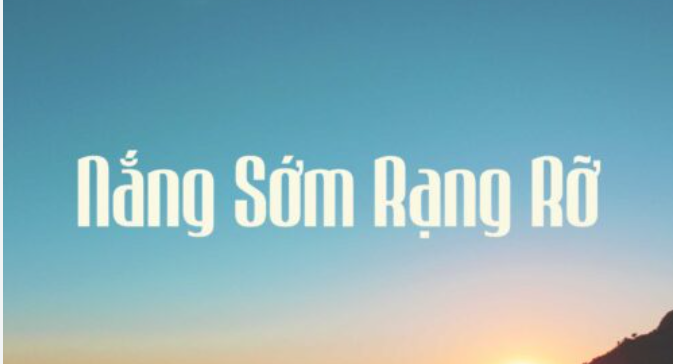
SVN Vantom là bộ phông chữ thuộc dòng Modern Display mang phong cách thanh lịch, thời thượng và tràn đầy hơi thở nghệ thuật đương đại. Với những đường cong uốn lượn sắc sảo, tỉ lệ chữ phá cách kết hợp cùng hệ thống ký tự nối (ligatures) độc bản, phông chữ này là lựa chọn hàng đầu cho các thiết kế logo thời trang xa xỉ, bìa tạp chí danh tiếng và bao bì mỹ phẩm cao cấp. Doozypack.vn cung cấp link tải font SVN Vantom Việt hóa chuẩn kỹ thuật, giúp bạn sở hữu phông chữ đẳng cấp mà không lo gặp bất kỳ lỗi hiển thị dấu thanh nào khi thiết kế in ấn.
Đặc điểm thẩm mỹ độc đáo của bộ font SVN Vantom
Vantom không đi theo sự khuôn mẫu của các phông chữ hình học thông thường; nó mang đến một ngôn ngữ thị giác đầy tính duy mỹ, kết hợp giữa sự tối giản hiện đại và nét mềm mại gợi cảm.
Phong cách Display hiện đại với những đường cong quyến rũ
Đặc trưng lớn nhất của SVN Vantom Font là sự biến tấu tài tình ở những điểm giao nét. Cấu trúc chữ có độ tương phản thanh đậm vừa phải, các nét thẳng đứng vững chãi kết hợp cùng các góc bo mềm mại ở những ký tự như ‘a’, ‘g’, ‘r’, tạo nên một nhịp điệu Typography vô cùng cuốn hút. Khi đặt Vantom làm tiêu đề trên bao bì, thương hiệu của bạn sẽ ngay lập tức toát lên vẻ ngoài sang trọng, đắt tiền và đậm chất thẩm mỹ châu Âu.
Hệ thống ký tự ghép đôi (Ligatures) nghệ thuật và độc bản
Một điểm khiến các nhà thiết kế chuyên nghiệp luôn săn đón font chữ SVN Vantom Font chính là kho ký tự ghép đôi vô cùng phong phú. Phông chữ cho phép bạn liên kết hai hoặc ba chữ cái lại với nhau một cách tự nhiên và liền mạch, biến những dòng chữ thương hiệu đơn giản thành một biểu tượng đồ họa tinh xảo mà không cần phải tốn nhiều giờ chỉnh sửa thủ công.
Ưu điểm nổi bật của bản font Việt hóa SVN Vantom
Khi ứng dụng các phông chữ nghệ thuật quốc tế vào thị trường trong nước, sự chỉn chu về dấu câu là yếu tố quyết định đến tính chuyên nghiệp của bản thiết kế:
- Khắc phục triệt để lỗi dấu tiếng Việt: Phiên bản font Việt hóa SVN Vantom đã được đội ngũ SVN trau chuốt thủ công từng dấu câu. Các dấu sắc, huyền, hỏi, ngã, nặng được vẽ thanh mảnh, đặt ở vị trí cân đối so với thân chữ, không gây cảm giác chắp vá hay va chạm vào các đường nét uốn lượn xung quanh.
03 Ứng dụng thực tế của SVN Vantom Font trong sản xuất bao bì
Sự kiêu sa và thanh lịch của Vantom mang lại hiệu ứng thị giác đắt giá trên các dòng sản phẩm bao bì thực tế do Doozypack.vn sản xuất:
- Hộp giấy mỹ phẩm & Nước hoa: Tên dòng sản phẩm in bằng nét chữ Vantom kết hợp kỹ thuật ép kim nhũ vàng trên giấy Ivory cán màng mờ tạo nên vẻ đẹp sang trọng chuẩn quốc tế.
- Túi giấy thời trang cao cấp: Tiêu đề thương hiệu in bằng font Vantom màu đen tối giản trên nền túi giấy trắng giúp cửa hàng toát lên gu thẩm mỹ tinh tế và đẳng cấp.
- Tem nhãn nến thơm & Tinh dầu cao cấp: Cấu trúc chữ thanh thoát giúp nhãn dán chai lọ trông như một tác phẩm thủ công được chăm chút tỉ mỉ bởi nghệ nhân.
03 Lưu ý kỹ thuật khi in ấn với phông chữ nghệ thuật SVN Vantom
Việc sản xuất bao bì thực tế sử dụng các phông chữ có đường nét tinh xảo như Vantom đòi hỏi sự am hiểu kỹ thuật chuyên sâu tại xưởng in Doozypack.vn:
- Kiểm soát độ dày nét Hairline khi ép kim: Các nét vuốt đuôi nối chữ của font chữ này khá thanh mảnh. Khi gia công ép kim vàng (Hot Stamping), designer nên đảm bảo nét chữ có độ dày tối thiểu 0.15mm để nhũ bám dính sắc nét, không bị đứt đoạn.
- Chọn chất liệu giấy phẳng mịn: Vantom đẹp nhất khi in trên giấy Ivory, Couche hoặc giấy mỹ thuật nhẵn. Tránh in các nét chữ quá thanh trên bề mặt giấy Kraft thô nhám vì mực dễ bị loang làm mất đi độ sắc sảo của nét chữ.